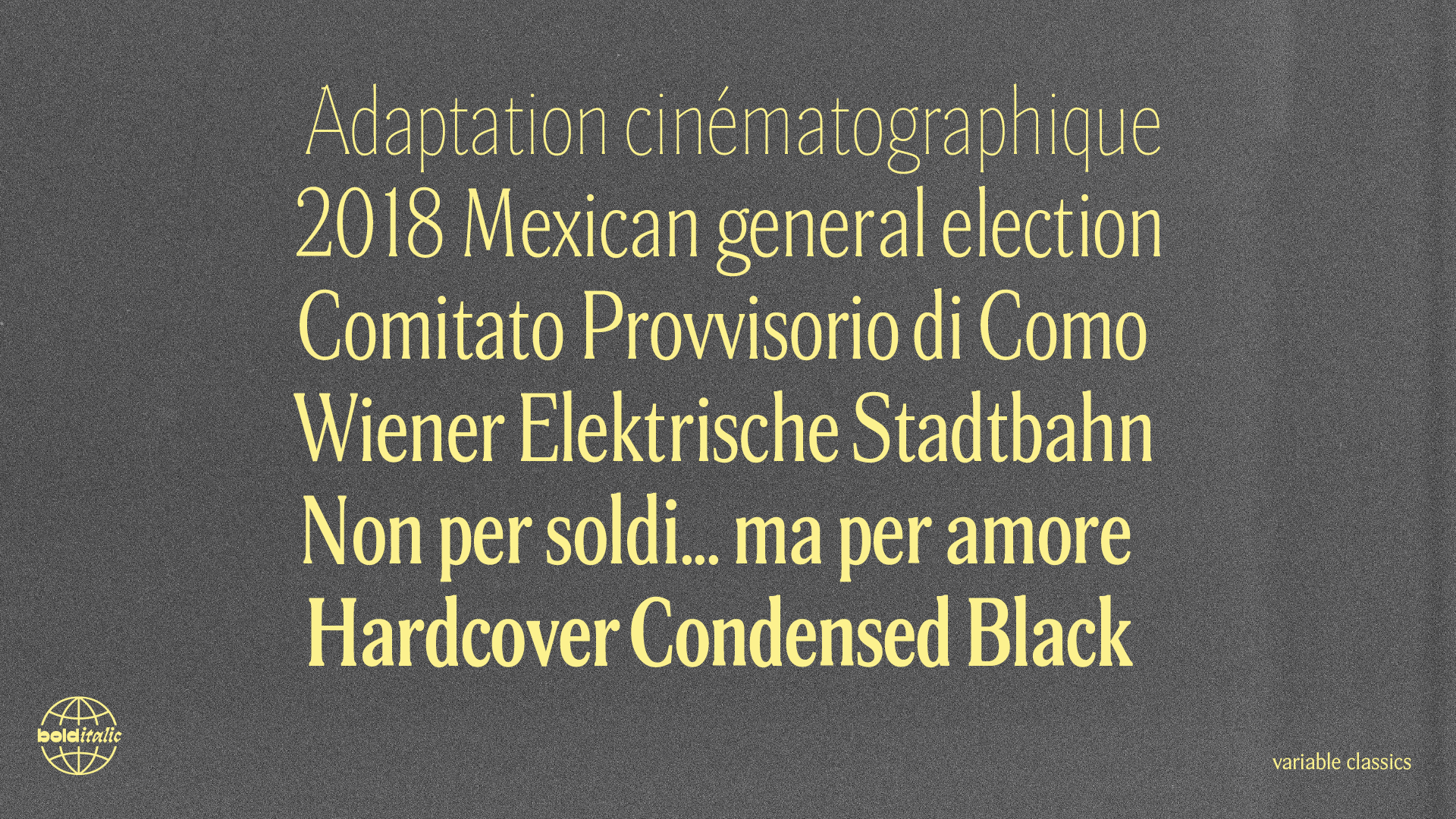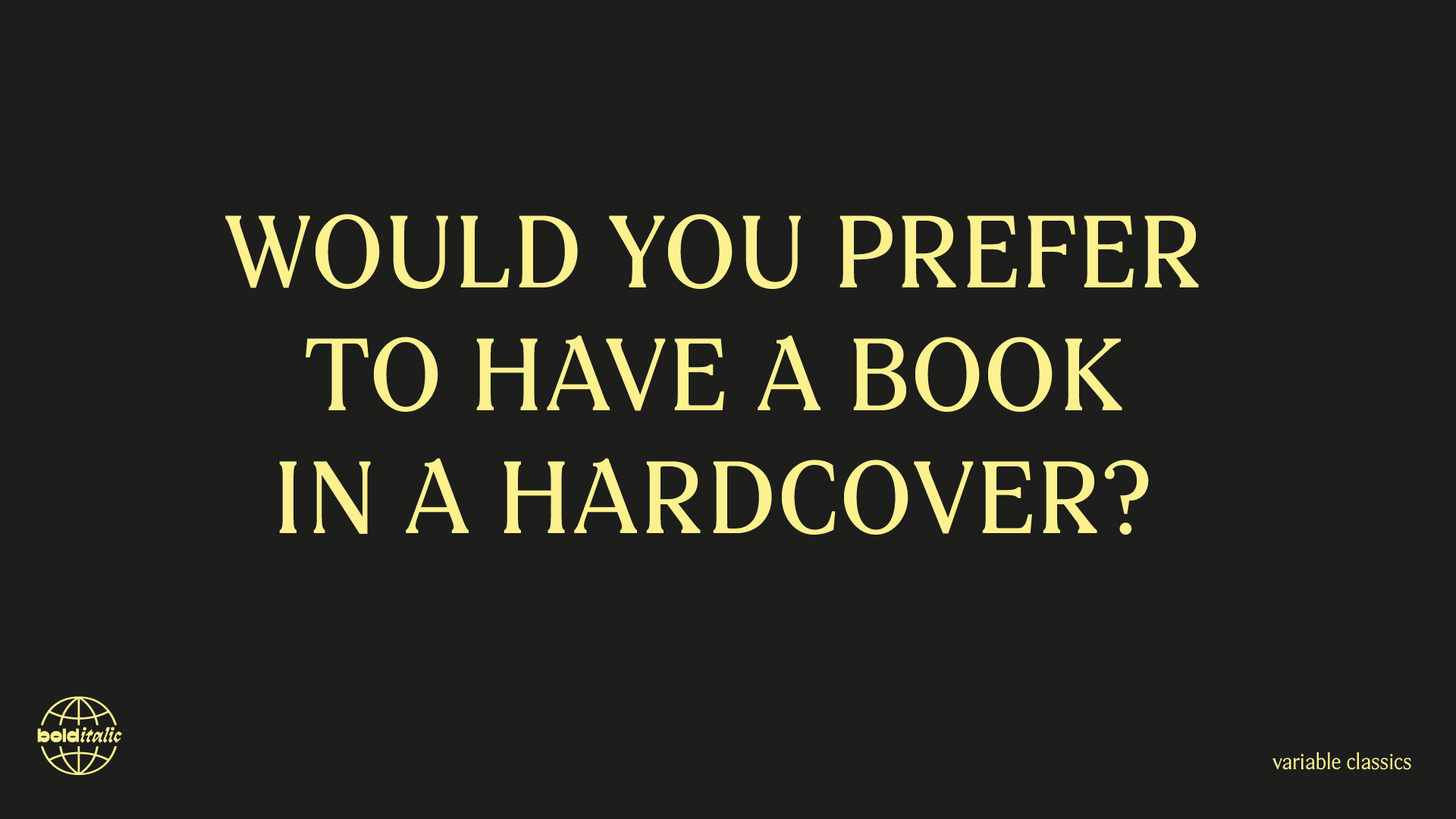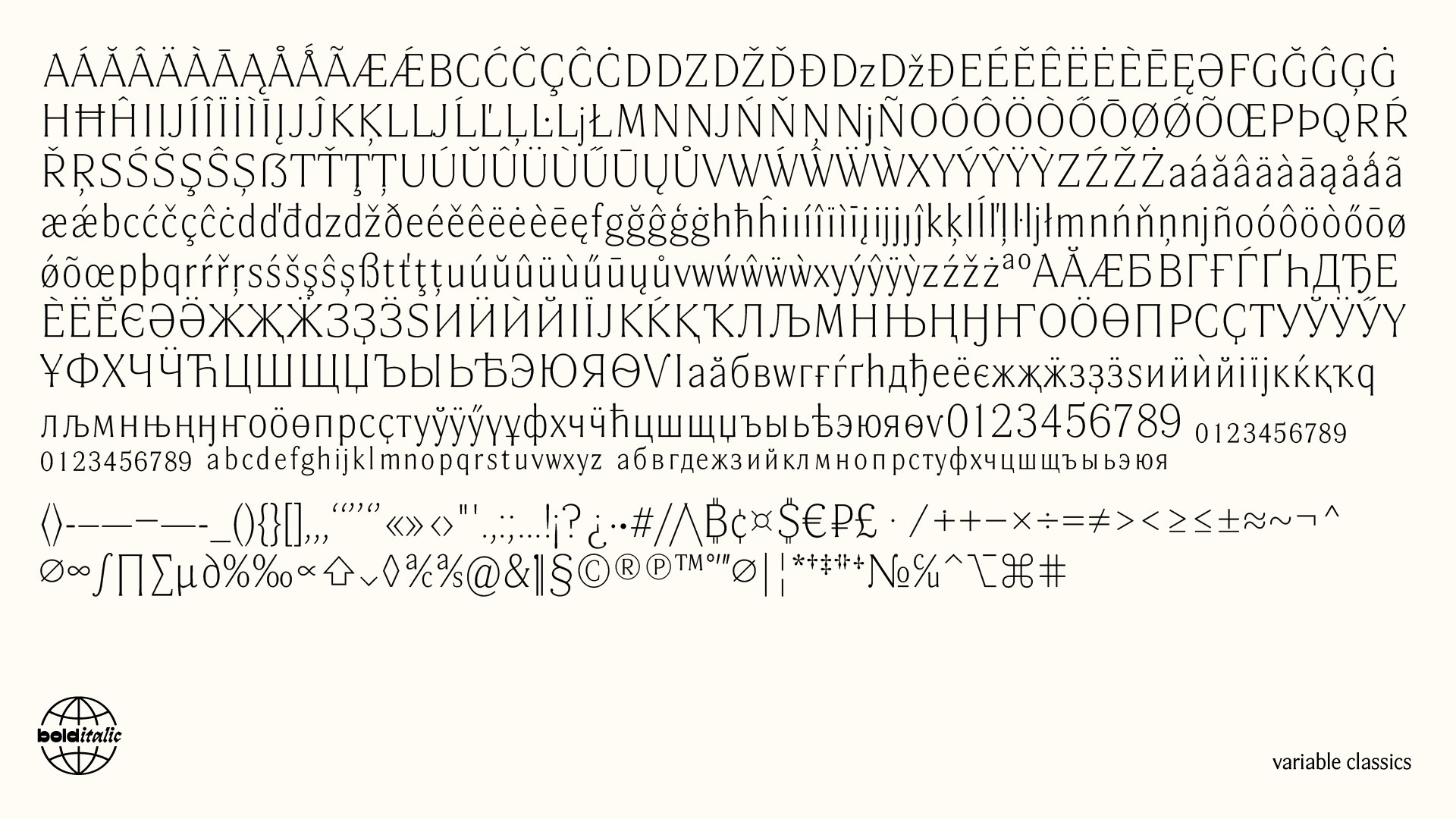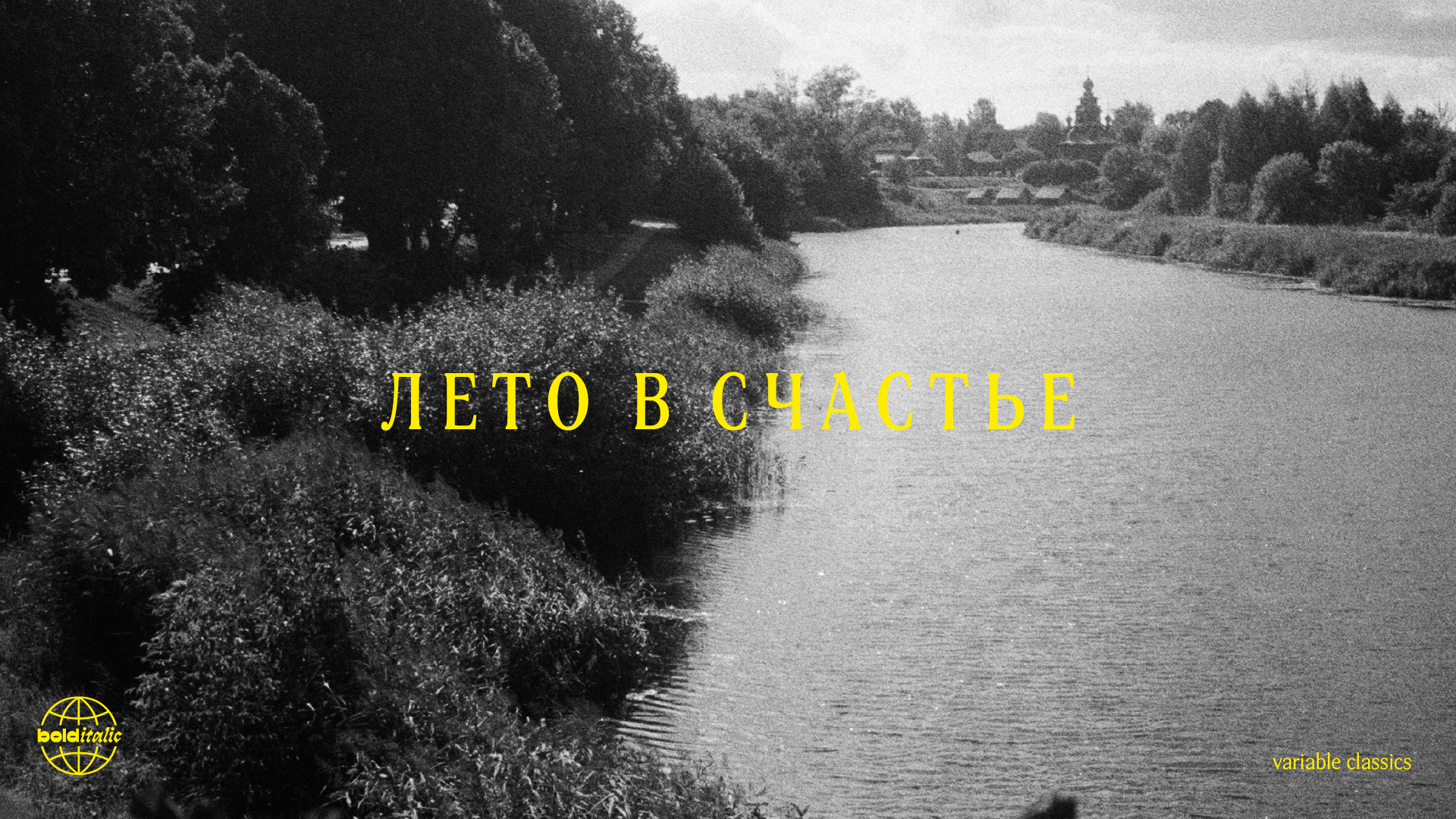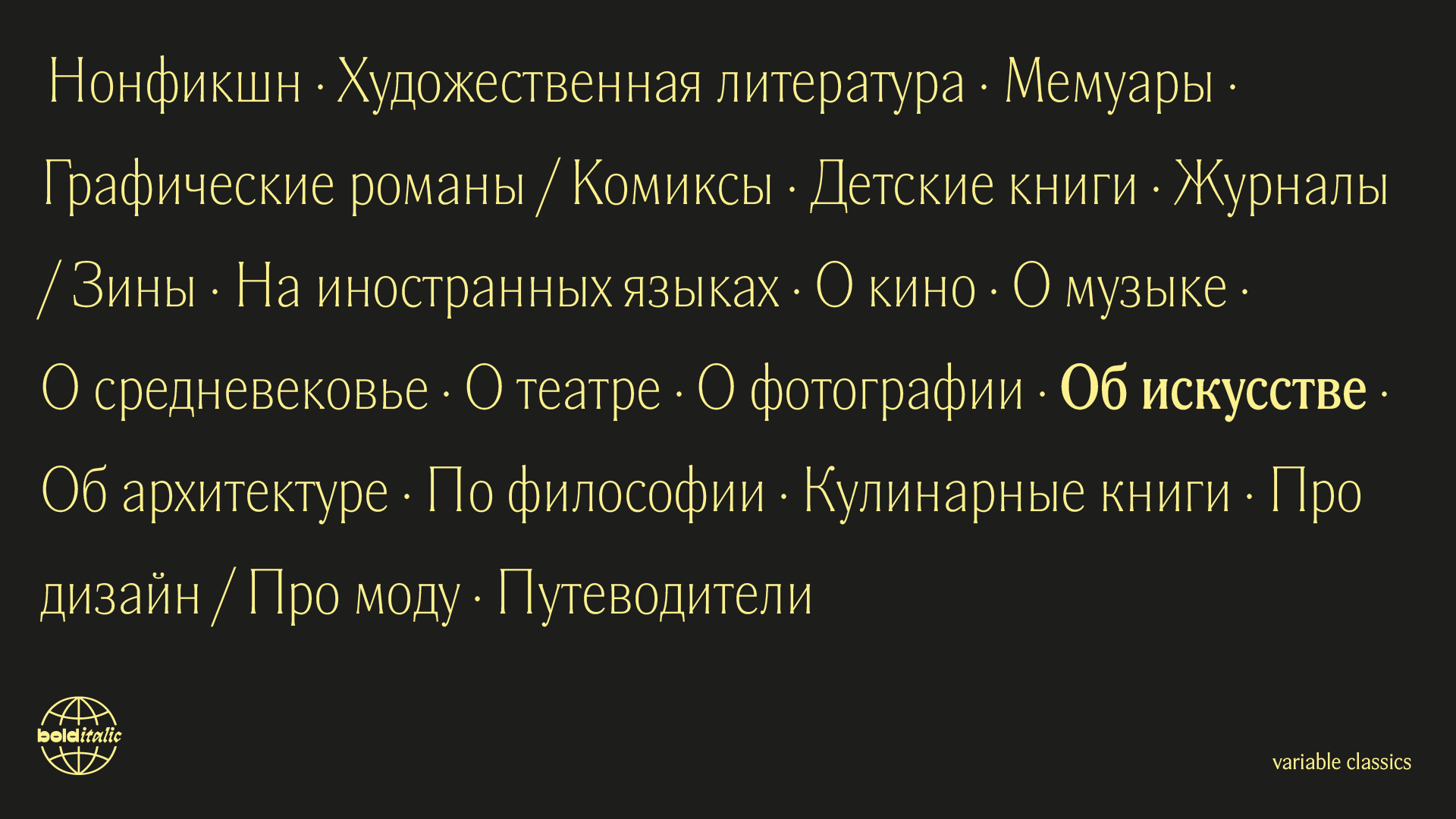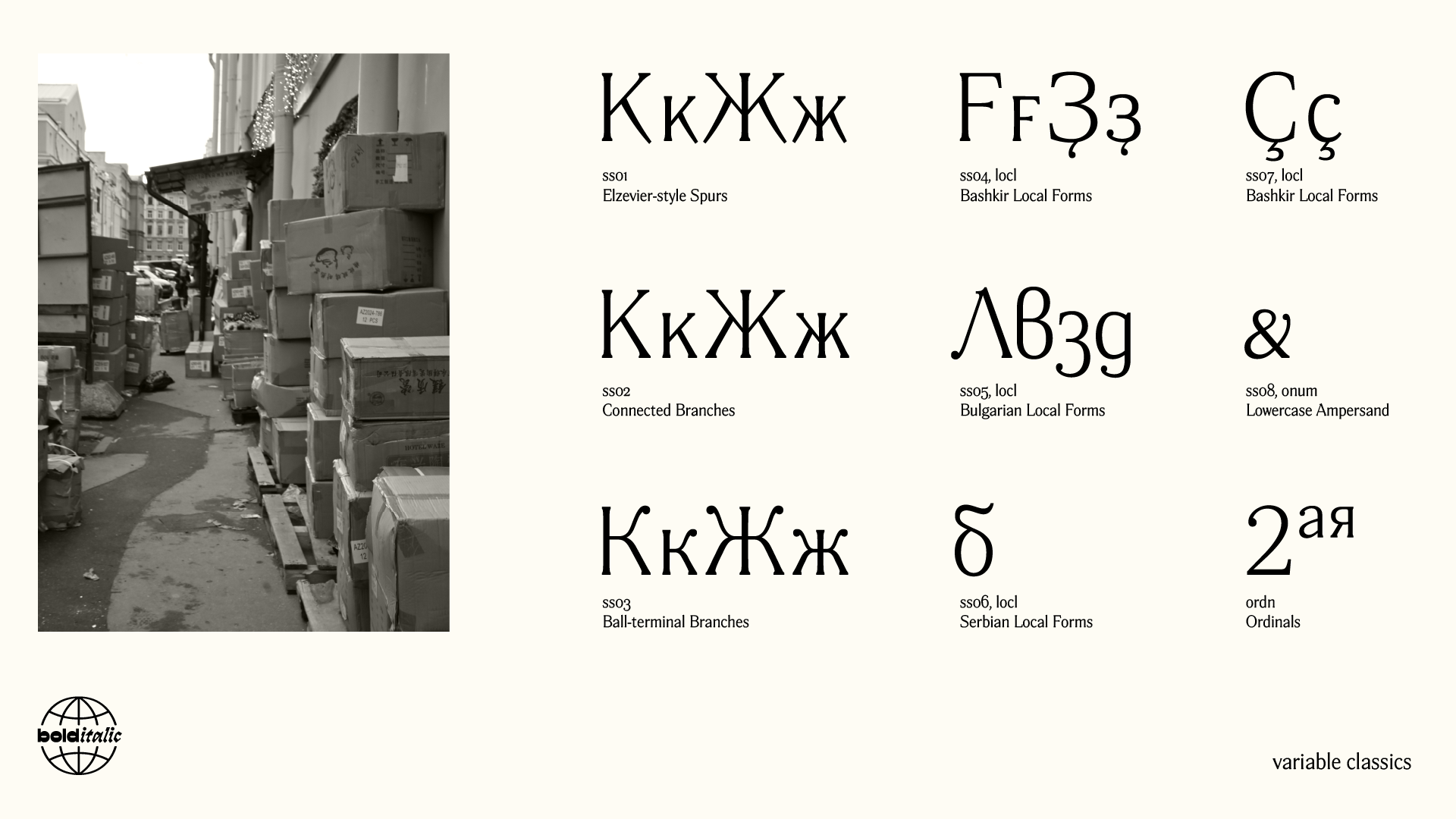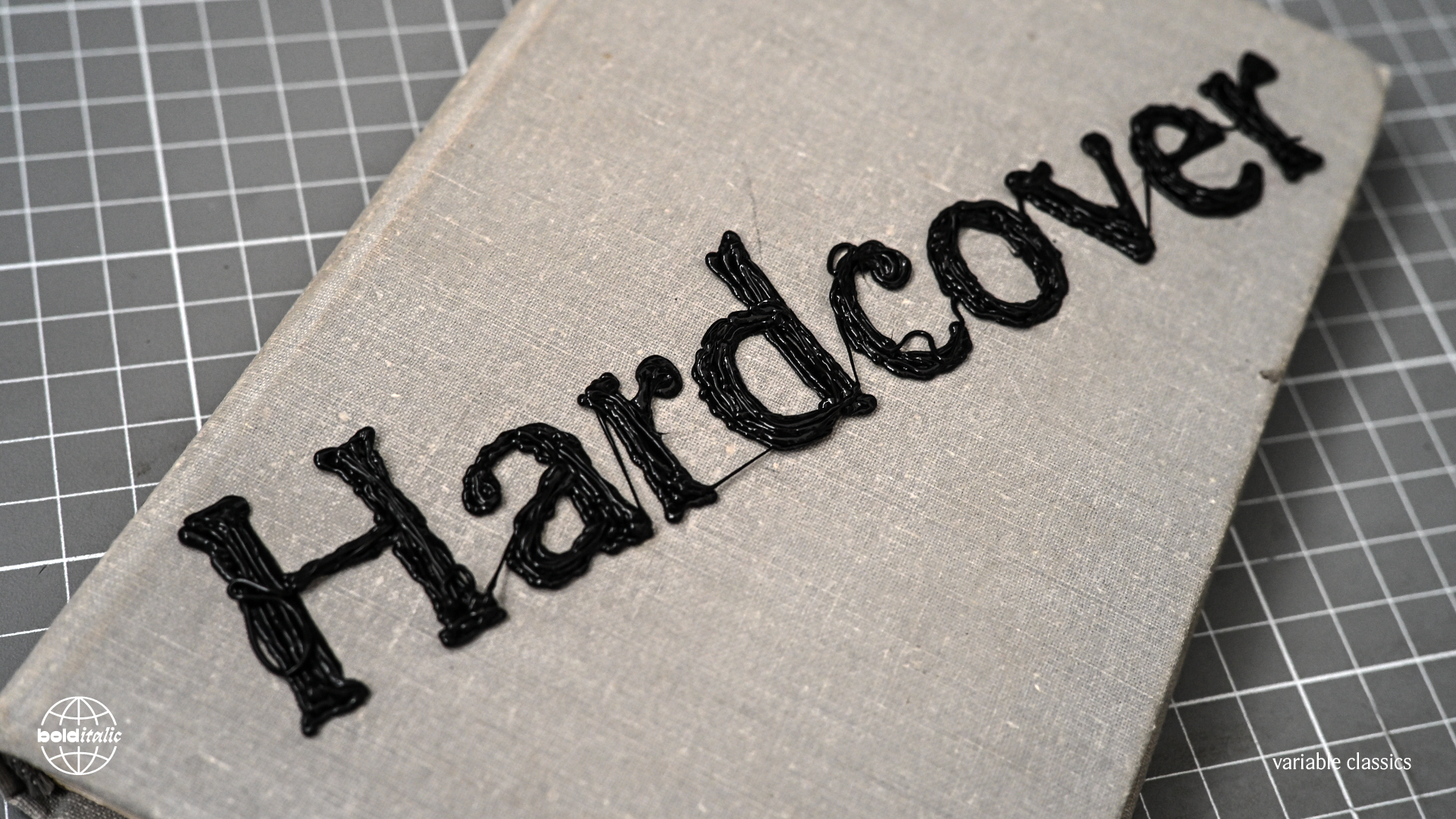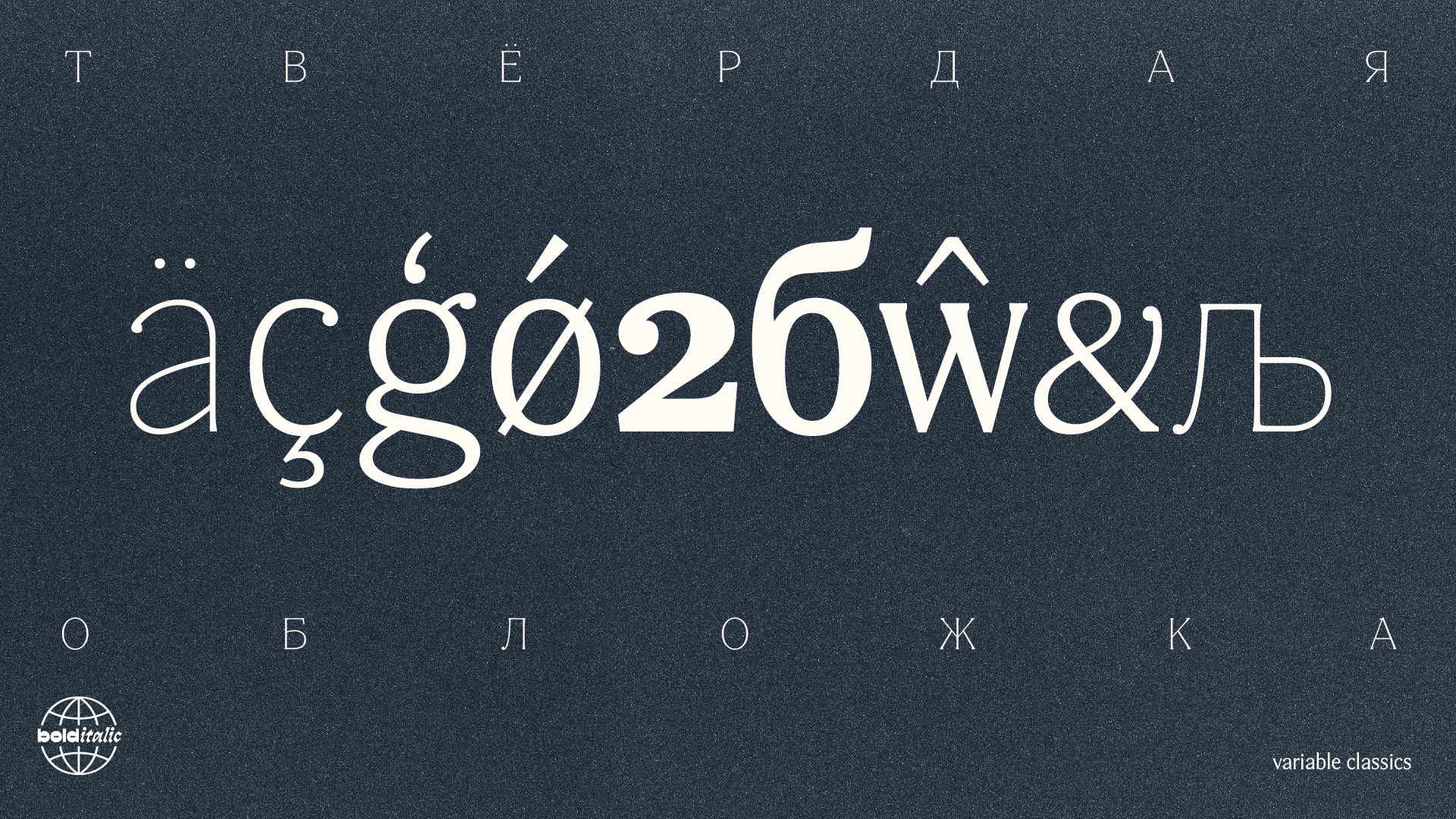
Hardcover
Гарнитура «Твёрдая обложка» или Hardcover — переосмысление наследия эльзевиров ХХ века, начиная со шрифтов словолитни Бертгольда, сквозь все вариации Литературной НИИ Полиграфмаш, до современных цифровых ревайвалов. Набор может быть как хáрактерным, с традиционными для эльзевиров шпорами (ss02), более нейтральным (по умолчанию), строгим (ss01) или старообразно-игривым, как в ранних версиях Латинского шрифта.
Вариативный шрифт имеет 2 оси: пропорций и насыщенности. Знаковый состав: языки Европы и народов России, минускульные и маюскульные цифры, регистрозависимая пунктуация, стилистические альтернативы, и прочее.